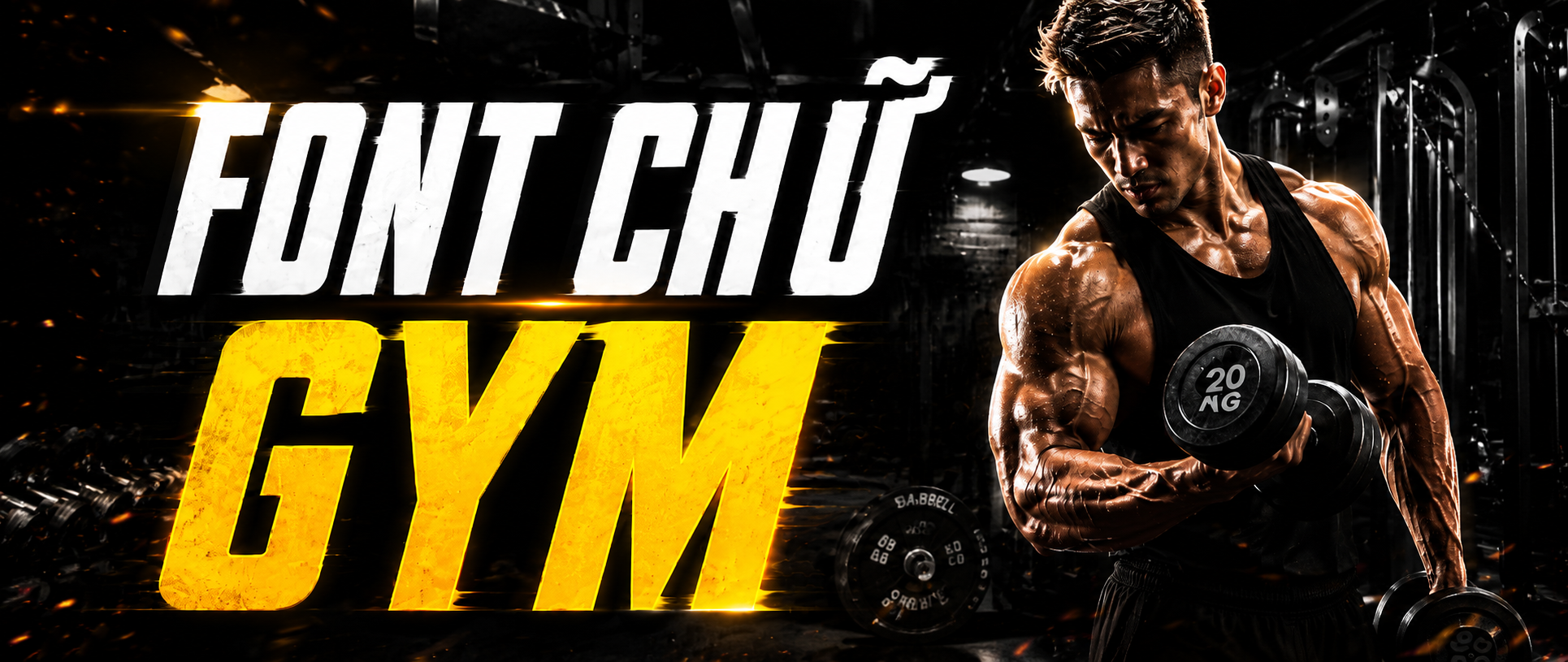
Gym và fitness là nhóm thiết kế cần tạo cảm giác năng lượng ngay từ cái nhìn đầu tiên. Một logo phòng gym, poster lớp tập, banner khai trương, bảng giá PT, áo team hay thumbnail thử thách 30 ngày đều cần chữ mạnh, rõ, có nhịp và đủ sức kéo mắt. Vì vậy, font chữ gym, fitness không nên chọn chỉ vì đẹp. Font phải thể hiện tinh thần vận động, sức bền, kỷ luật và sự tự tin.
Thiết kế gym thường dùng ảnh người tập, ánh sáng mạnh, nền tối, khói, kim loại, texture bê tông, màu đỏ, cam, đen hoặc xanh neon. Nếu font quá mảnh, chữ dễ chìm. Nếu font quá rối, người xem không kịp đọc nội dung ưu đãi, tên lớp, lịch tập hoặc CTA đăng ký.
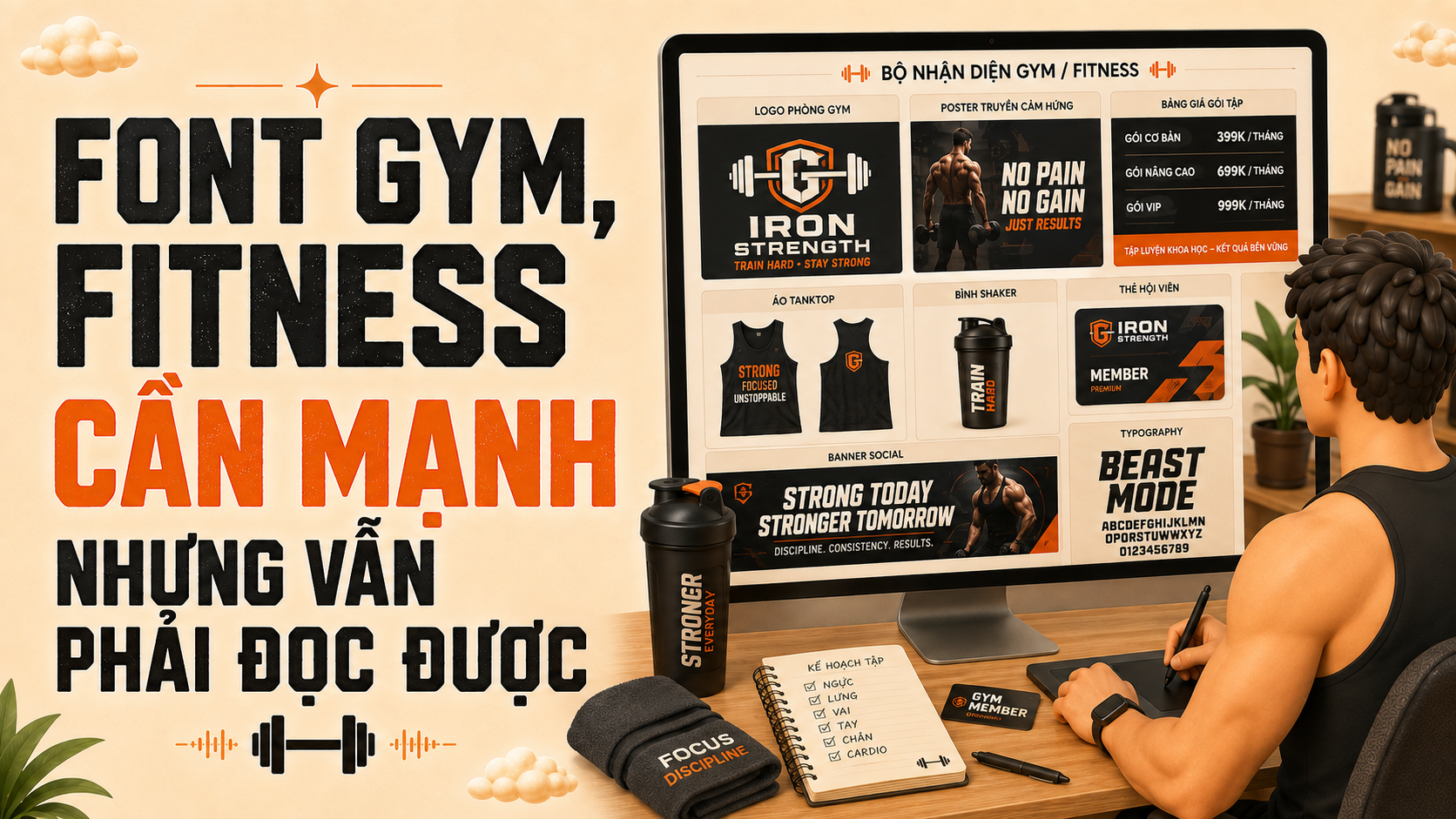
Một font gym tốt nên có nét chắc, khoảng cách chữ đủ thoáng, số dễ đọc và dấu tiếng Việt cân. Điều này đặc biệt quan trọng với các cụm như phòng tập thể hình, giảm mỡ, tăng cơ, huấn luyện cá nhân, thử thách 30 ngày, đăng ký hôm nay, lịch tập nhóm.
Font mạnh nhất không phải lúc nào cũng là font tốt nhất. Với logo hoặc headline, bạn có thể dùng display đậm. Nhưng với bảng giá, lịch lớp, mô tả gói tập và thông tin liên hệ, font sans-serif rõ sẽ hiệu quả hơn.
Biển phòng gym, standee, poster ngoài đường và bảng lịch lớp cần đọc được từ xa. Social ads và thumbnail challenge lại cần rõ khi xem trên mobile. Hãy thử font ở cả kích thước lớn, nhỏ và trên nền ảnh thật trước khi dùng.
Gym nam tính, boxing và crossfit hợp font góc cạnh, mạnh. Fitness studio dành cho nữ có thể dùng sans-serif hiện đại, gọn và sáng. Yoga, pilates hoặc wellness cần mềm hơn, nhưng vẫn không nên quá bay bổng nếu thông tin cần đọc nhanh.
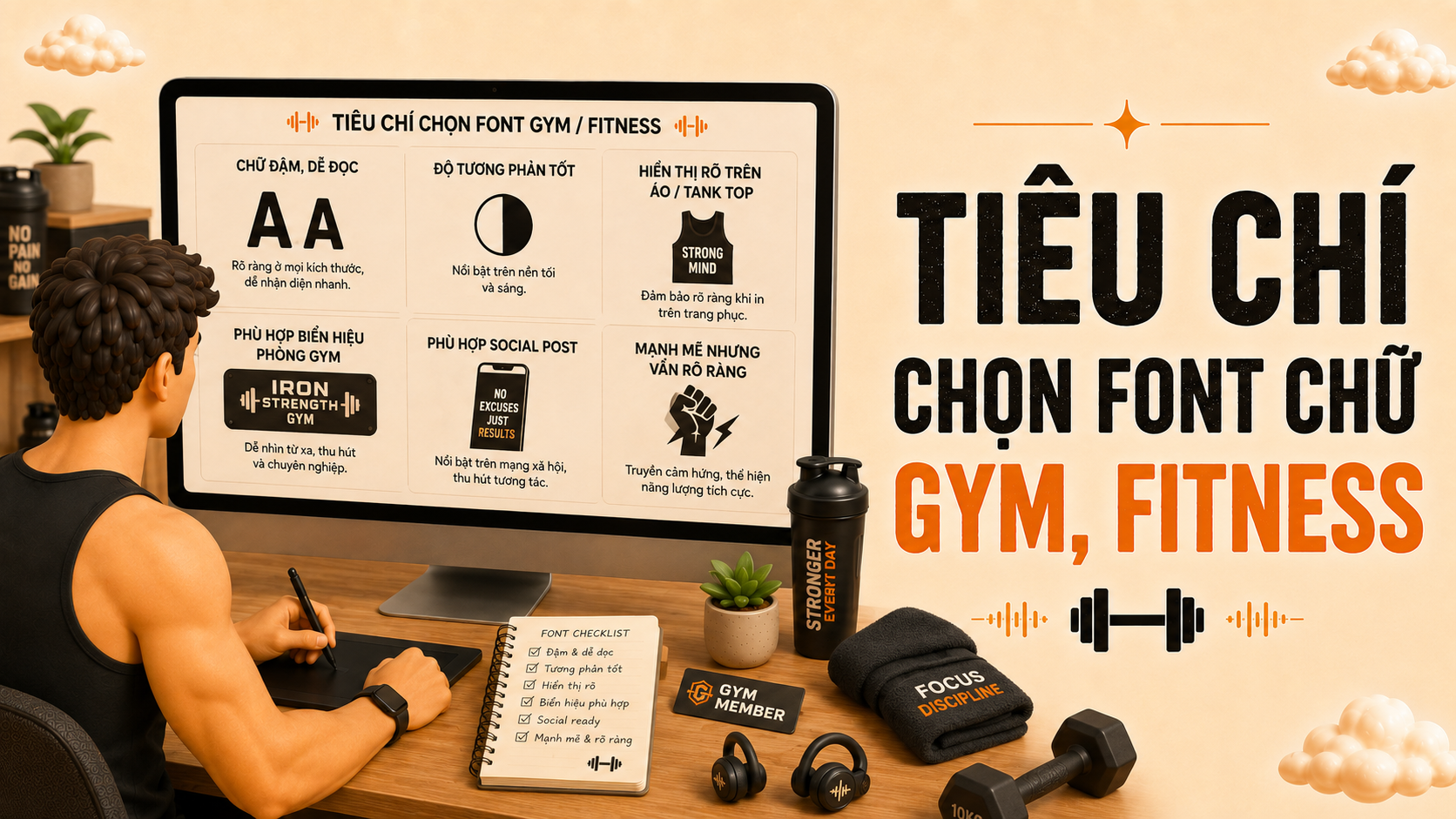
Nhiều font display mạnh có thể đẹp ở chữ tiếng Anh nhưng lỗi dấu khi gõ tiếng Việt. Với S99, hãy ưu tiên font Việt hóa để các dấu sắc, huyền, hỏi, ngã, nặng không bị lệch khi dùng cho headline lớn.
Một phòng gym không chỉ có logo. Bạn còn cần font cho áo staff, thẻ hội viên, bảng giá, lịch lớp, poster khuyến mãi, story, landing page, voucher và bảng nội quy. Font nên đủ linh hoạt để dùng nhiều điểm chạm.
Nhóm font display mạnh phù hợp với logo phòng gym, poster giảm mỡ, banner khai trương, thumbnail video tập luyện, challenge 30 ngày, lớp boxing hoặc crossfit. Nét chữ chắc giúp thiết kế có lực và nổi bật trên nền ảnh người tập.
Hãy dùng nhóm này cho headline ngắn như Tăng cơ, Đốt mỡ, Bứt phá giới hạn, 30 ngày thay đổi, Boxing night, Fit challenge. Không nên nhồi quá nhiều chữ vào một headline. Nếu tiêu đề dài, hãy tách dòng và dùng font phụ rõ hơn cho phần giải thích.
Sans-serif là nhóm font nền quan trọng nhất trong hệ thống gym. Dù logo dùng font mạnh, phần bảng giá, lịch lớp, hướng dẫn tập, nội quy, mô tả gói hội viên, thông tin PT và CTA vẫn cần font dễ đọc. Đây là phần ảnh hưởng trực tiếp đến chuyển đổi.
Bạn có thể dùng sans-serif cho các dòng như Gói 1 tháng, Gói PT 12 buổi, Lịch lớp HIIT, Yoga, Boxing, Đăng ký ngay, Hotline, Địa chỉ. Khi thiết kế bảng giá, nên dùng weight semibold cho giá và regular cho mô tả để người đọc quét thông tin nhanh.
Công thức 1 là display mạnh plus sans-serif. Dùng font mạnh cho logo, headline, poster challenge; dùng sans-serif cho bảng giá, lịch lớp, CTA và thông tin liên hệ. Đây là công thức an toàn nhất cho phòng gym phổ thông.
Công thức 2 là luxury sans-serif plus sans-serif rõ. Dùng font sang cho fitness studio, PT cá nhân, thương hiệu đồ tập; dùng font phụ rõ cho landing page, menu gói tập và profile huấn luyện viên.
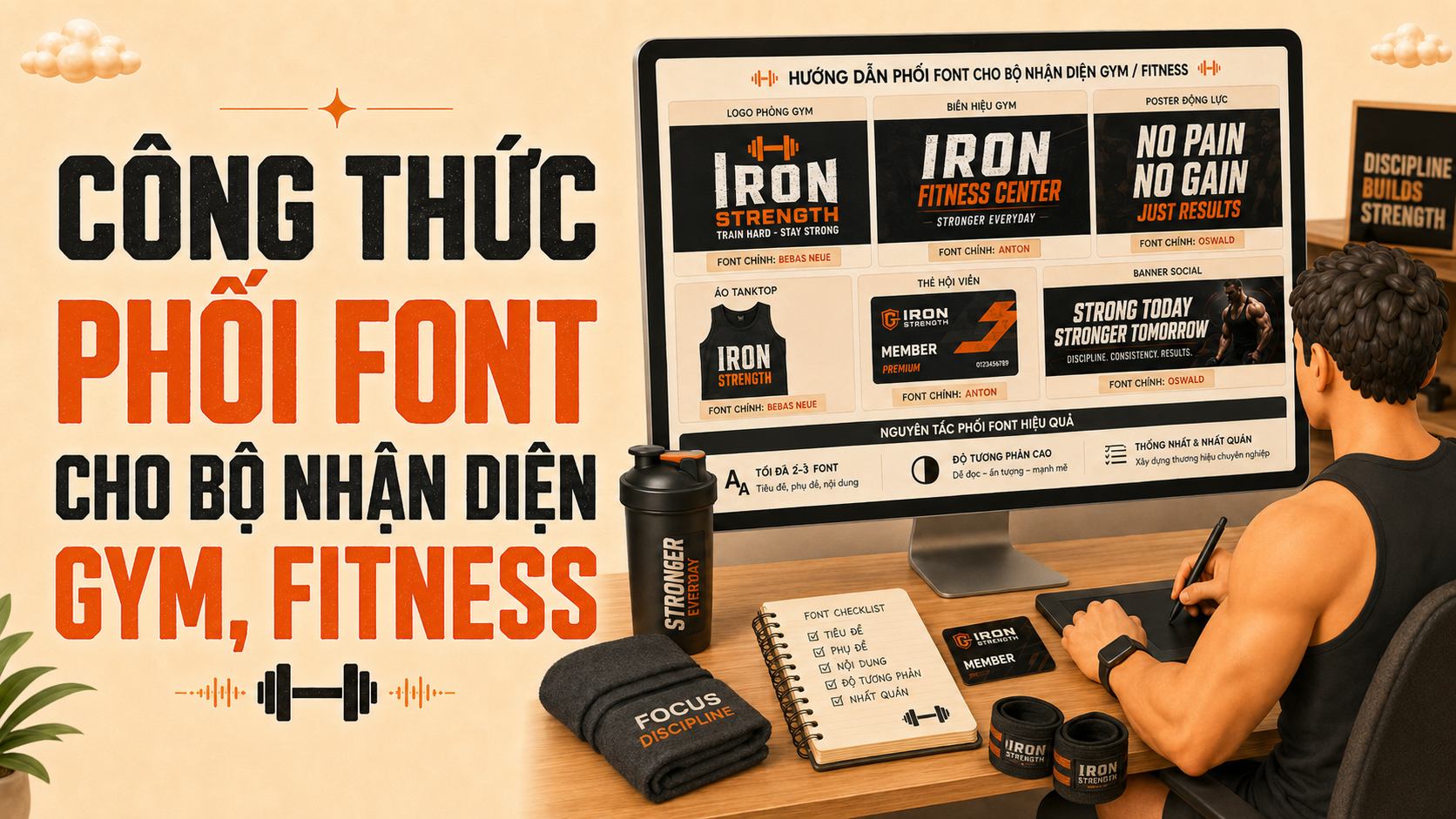
Công thức 3 là font năng động plus sans-serif. Dùng font vui cho lớp nhóm hoặc cộng đồng fitness; dùng font phụ rõ cho lịch, địa điểm và giá. Công thức này hợp các chiến dịch dễ tham gia hơn là thương hiệu quá hầm hố.
Không nên dùng quá 3 font trong một hệ thống. Nếu mỗi poster gym dùng một kiểu chữ khác nhau, thương hiệu sẽ thiếu nhận diện. Hãy chọn 1 font chính, 1 font phụ và 1 font nhấn cho campaign đặc biệt.
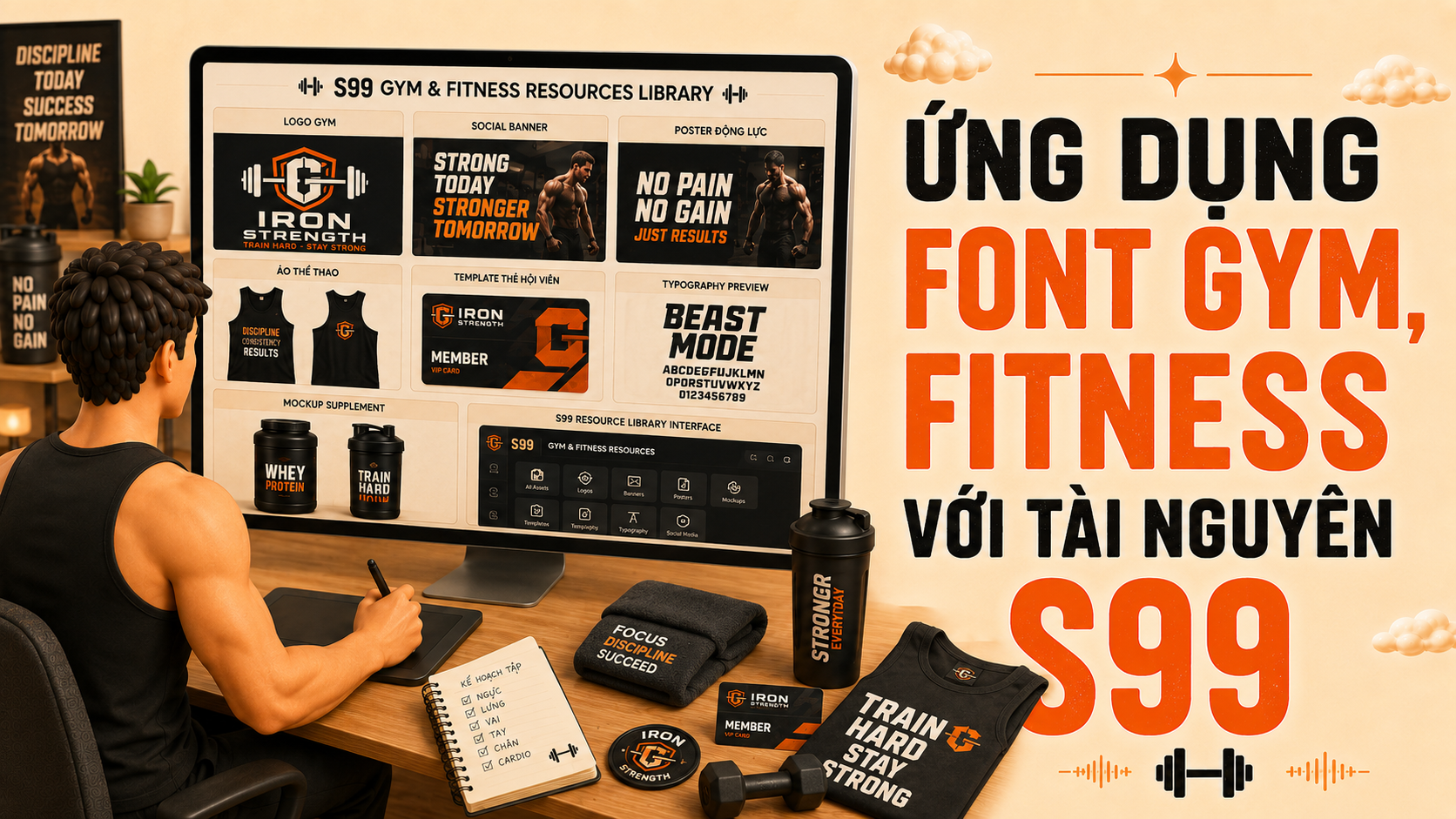
Font chữ gym, fitness tốt phải tạo cảm giác mạnh, rõ và có năng lượng, nhưng vẫn đủ dễ đọc để dùng trên logo, biển hiệu, poster, bảng giá, áo team, social ads và landing page. Hãy dùng font display cho điểm nhấn, sans-serif cho thông tin, luxury font cho studio cao cấp và font vui cho lớp nhóm cộng đồng.